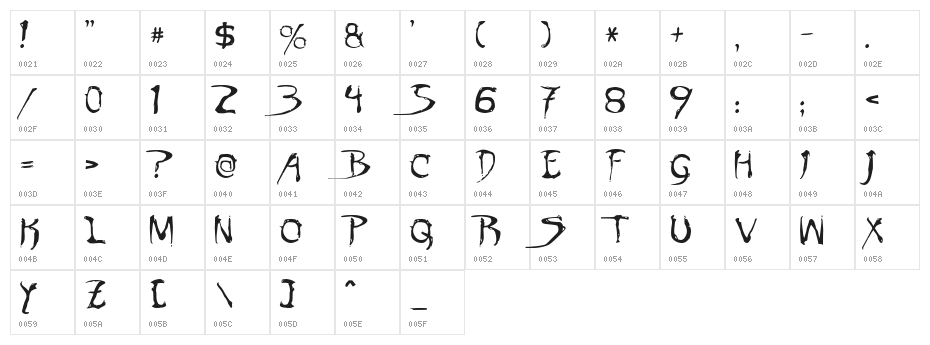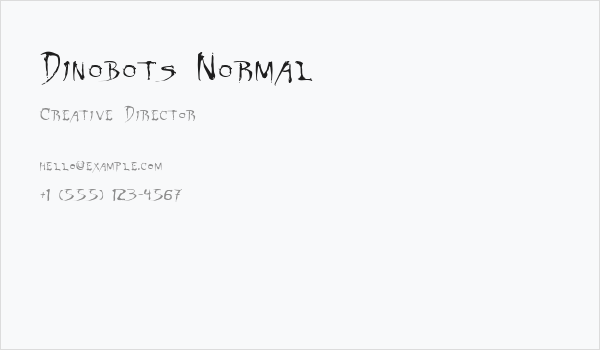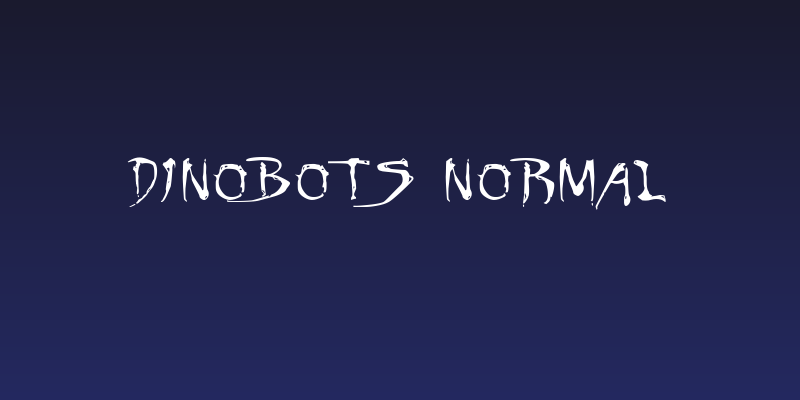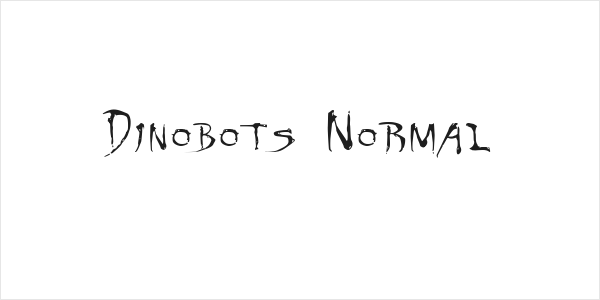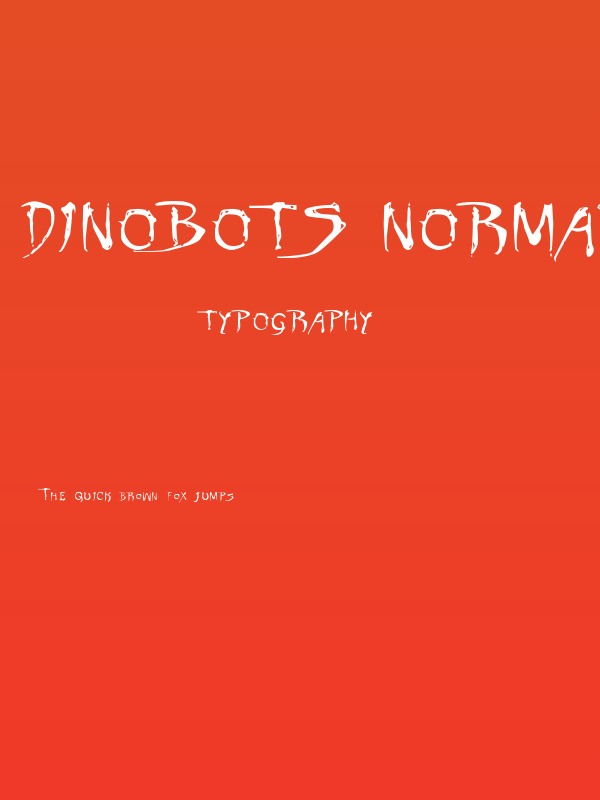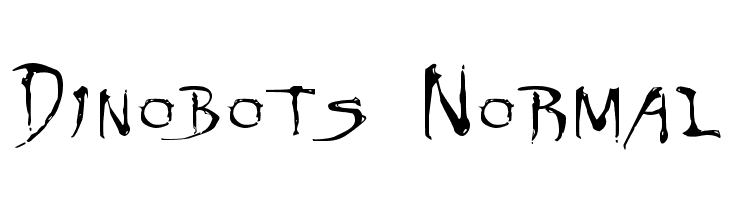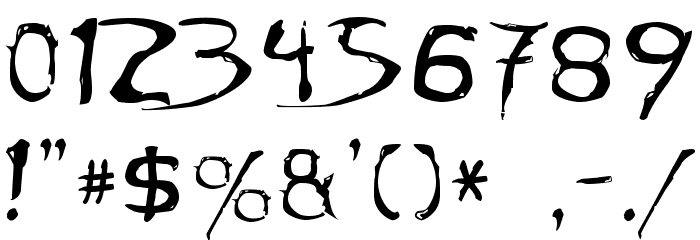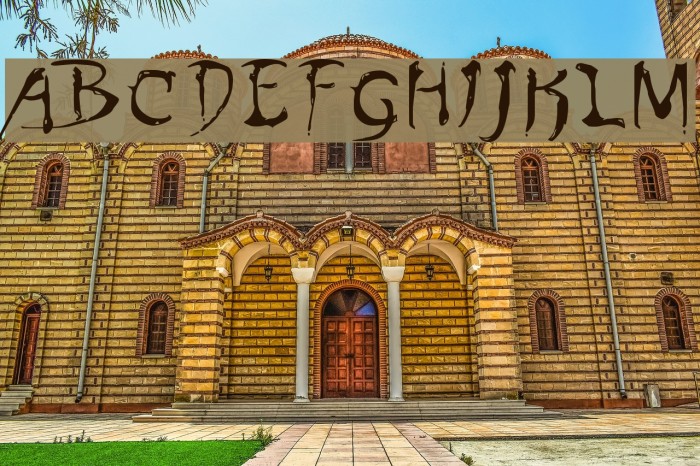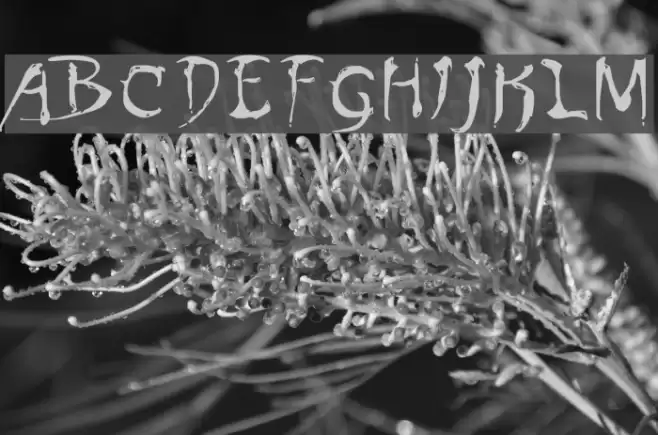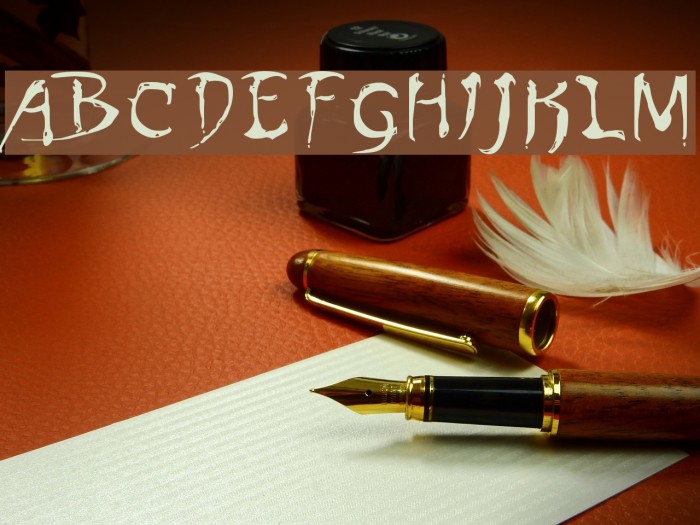
Dinobots Normal Font
| Vorgeschlagene Projekte | Ideal for posters, video game titles, movie logos, and any project requiring a strong, impactful visual style. |